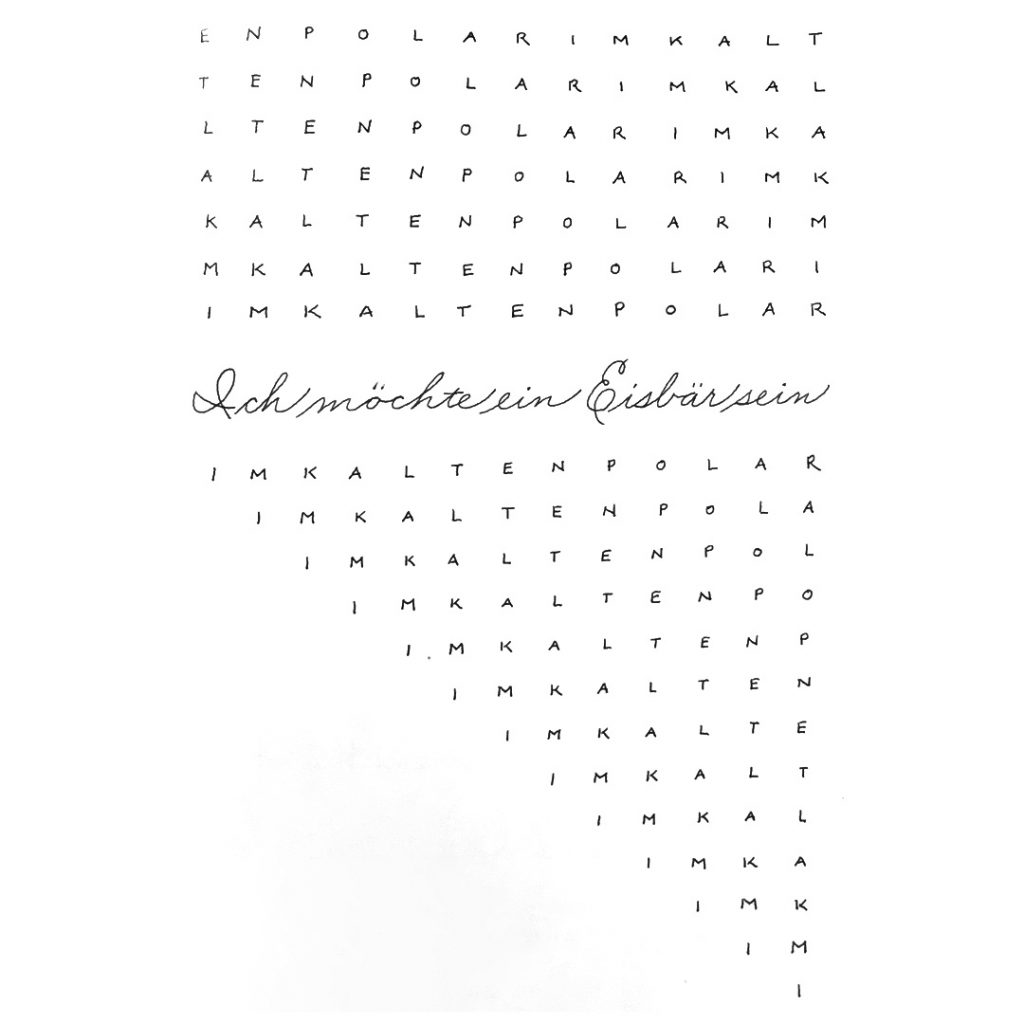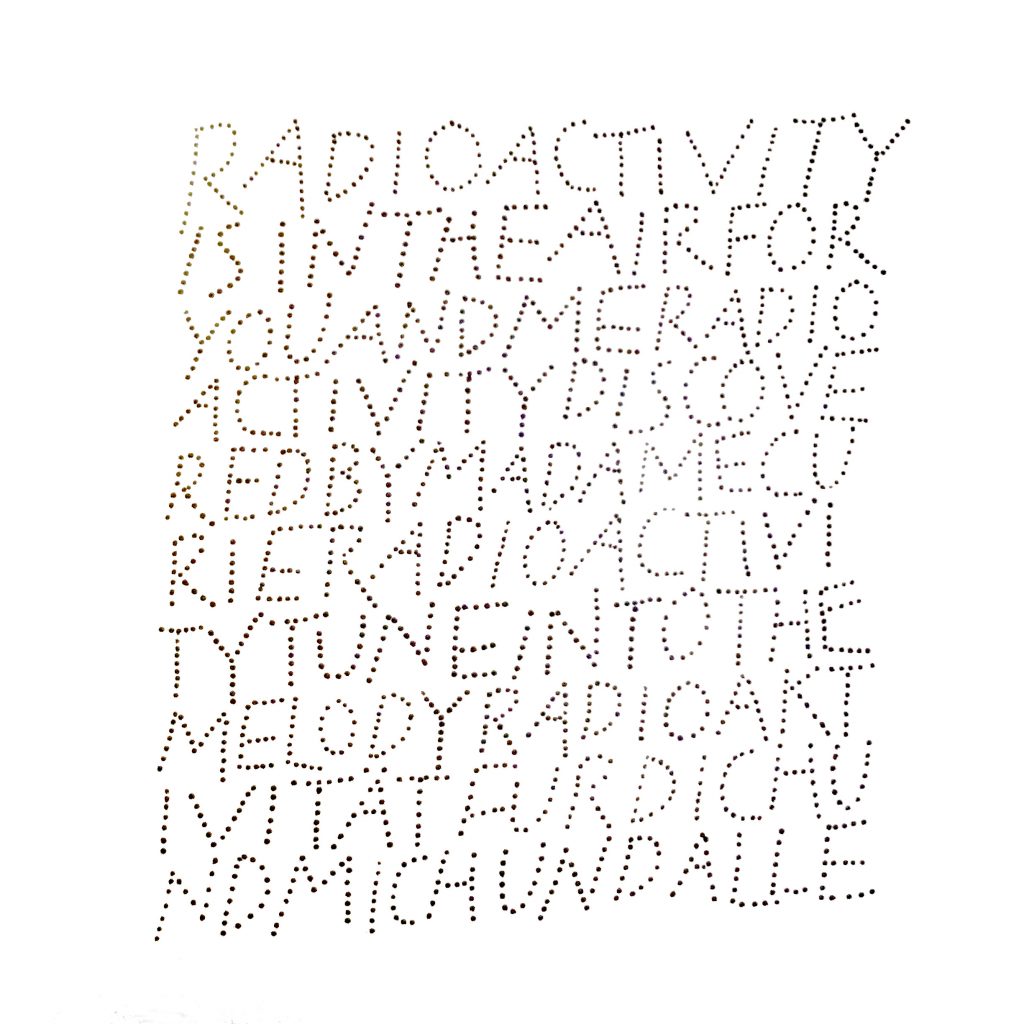
J’avais prévu de vous faire un article sur la Spencerian, cette écriture américaine à la plume pointue que je travaille assidûment depuis début septembre, mais j’ai saturé. Besoin d’une échappée après des semaines de rigueur spencerienne. Besoin de m’amuser un peu aussi, toujours avec des lettres, de façon consciente mais ludique. Je partage avec vous quelques « Jeux d’écriture » réalisés ces derniers jours.
Le terme de « jeux d’écriture » évoque certainement pour vous les travaux de Denise Lach. Je vous recommande d’ailleurs son très beau livre si vous ne l’avez pas déjà. Ses travaux s’inspirent des textures de la nature, réinterprétées en lettres avec différents outils. Très libre et graphique, le travail de Denise Lach est souvent en noir et blanc, mettant en évidence le plein et le vide, le rythme et le contraste.
De mon côté, je voulais quelque chose de très graphique, donc plutôt en noir et blanc aussi. J’ai travaillé avec des stylos tout bêtes, une bonne musique de fond et j’ai laissé mes résistances de côté pour travailler librement.
Jeux d’écriture 1
Jeux d’écriture 2
Plus de rondeurs dans les essais suivants…
Jeux d’écriture 3
Minimalisme inspiré de la musique electro que j’avais en fond sonore à ce moment-là (de la new wave allemande, allez je l’avoue, juste pour dire que ces compos nécessitent de se désinhiber un maximum, ah ah). Notez une petite phrase en Spencerian, quand même 😉
Jeux d’écriture 5
Jeux d’écriture 6
Ce dernier m’a fait un peu mal aux yeux. Il y a un exemple un peu similaire dans le livre de Denise Lach justement, qu’elle a réalisé en piquant le papier avec une aiguille. Moi j’ai simplement fait des pointillés !
Un essai en couleur que j’aime moins – je trouve que le noir et blanc est plus classe.
Jeux d’écriture 7
Et enfin, une citation d’une chanson de Madness – Baggy Trousers : « All we’ve learnt at school is how to bend not break the rules ». En français « Tout ce qu’on a appris à l’école c’est comment ployer, pas casser les règles ». Cette citation m’a inspirée dans le sens où pour casser les règles il faut d’abord les connaître et bien les maitriser il me semble. Ces planches très libres ont été faites en pensant à ce que j’avais appris lors de mes stages avec Yves Leterme, notamment sur les capitales dessinées : c’est apparemment spontané, ça l’est sans doute un peu, mais pas complètement…
Jeux d’écriture – Madness Baggy Trousers
Cette récréation suis un peu le même besoin et le même process que le travail sur les textures dont je vous avais déjà parlé. Il faut à la fois se lâcher, oser des trucs, tout en ayant en tête le design global (sinon ça part clairement en cacahuète et ça ne ressemble à rien). On veille notamment à l’équilibre de l’espacement, au contraste et aux contre-formes.
Même si poursuivre avec d’autres outils (calames, tires lignes, plumes…) me tente, pour le moment je crois que je vais poursuivre au feutre.